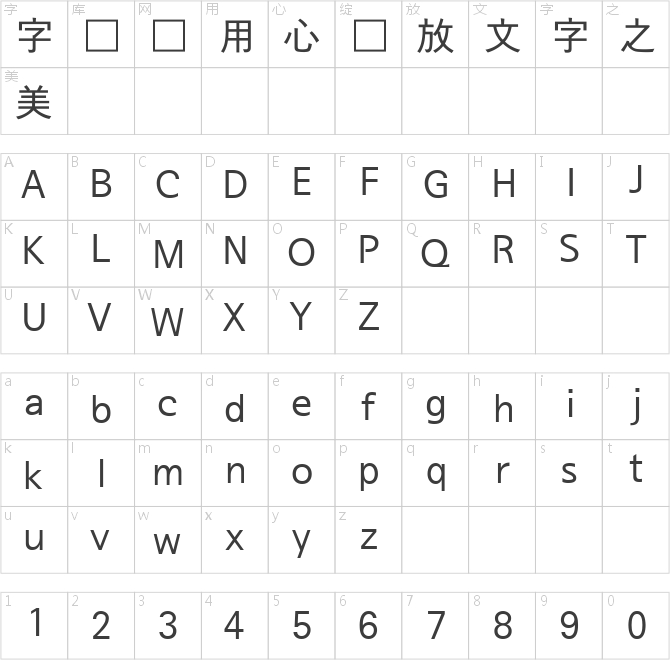
字體名稱: 首爾南山體
首爾南山體
首爾南山體介紹
首爾市為廣泛使用首爾的固有字體,提升城市認同性與品牌價值而開發出明體系列的4種首爾漢江體(Light、Medium、Bold、Extra Bold)和哥特體系列的4種首爾南山體(Light、Medium、Bold、Extra Bold)、1種豎寫體等共9種首爾字體。
首爾字體中蘊含著強韌的儒生精神與端莊的余白美,從造型上展現了韓屋的開放和瓦片的曲線美。此外,首爾字體取名時采用首爾兩大代表性資源“漢江”和“南山”,更能激發市民對韓民族固有美麗語言——韓文的文化自豪感。